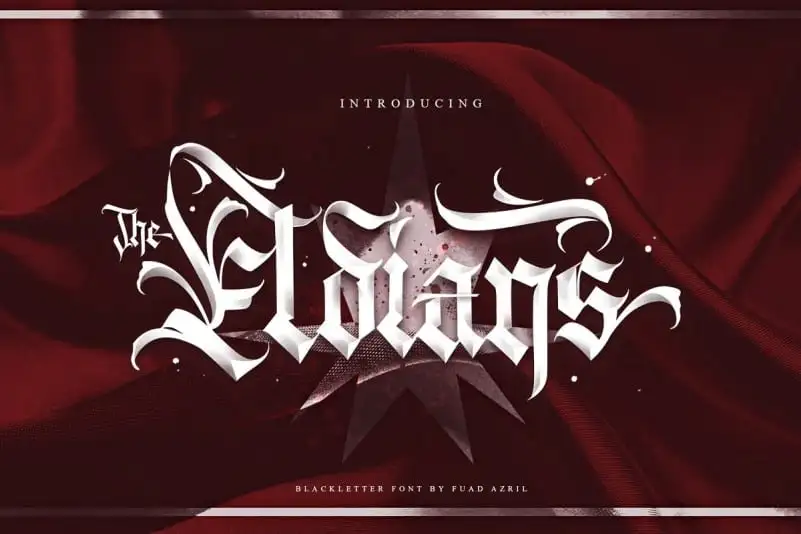
The Eldians Blackletter Font – Download Grátis
A ‘The Eldians Blackletter Font’ oferece uma experiência visual única para aqueles que buscam personalidade nas suas criações digitais. Desenvolvida pelo designer 99designs, essa fonte de estilo blackletter apresenta um impulso clássico e vintage, repleta de elementos decorativos e alternativas impressionantes. Suas características distintivas fazem dela uma escolha atraente para aplicativos como logotipos, rótulos de marca e designs de embalagens. A ‘The Eldians Blackletter Font’ é a fonte ideal para aqueles que buscam uma paixão única, transformando qualquer projeto em algo distinto e memorável.